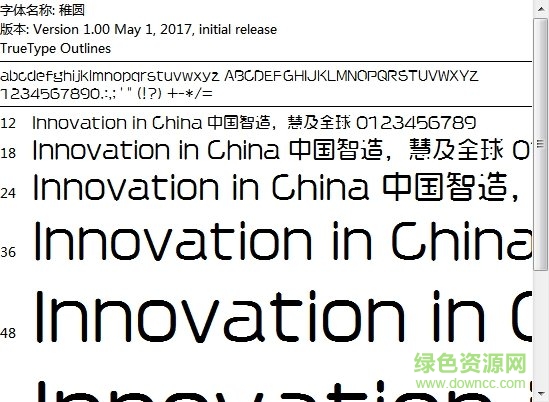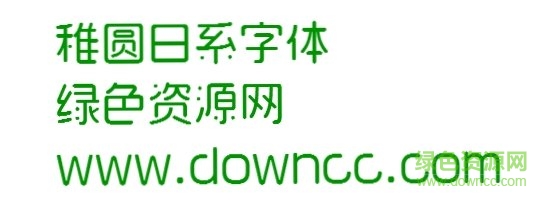
雉圓日系字體ttf是一款手機(jī)上提取出來(lái)的藝術(shù)字體,中文端正英文圓潤(rùn),都有著比較閱讀舒適、吸人眼球的視覺(jué)效果,來(lái)綠色資源網(wǎng)試試吧!
稚圓字體整體圓潤(rùn)飽滿,字形稚趣可愛(ài),既有圓體的規(guī)整,又帶有卡通字的靈動(dòng)活潑,字體中宮較大,所以看起來(lái)通透不顯擁擠。
稚圓字體原名 メガ丸,是一款日系字體,為了方便交流我將它取名為稚圓。